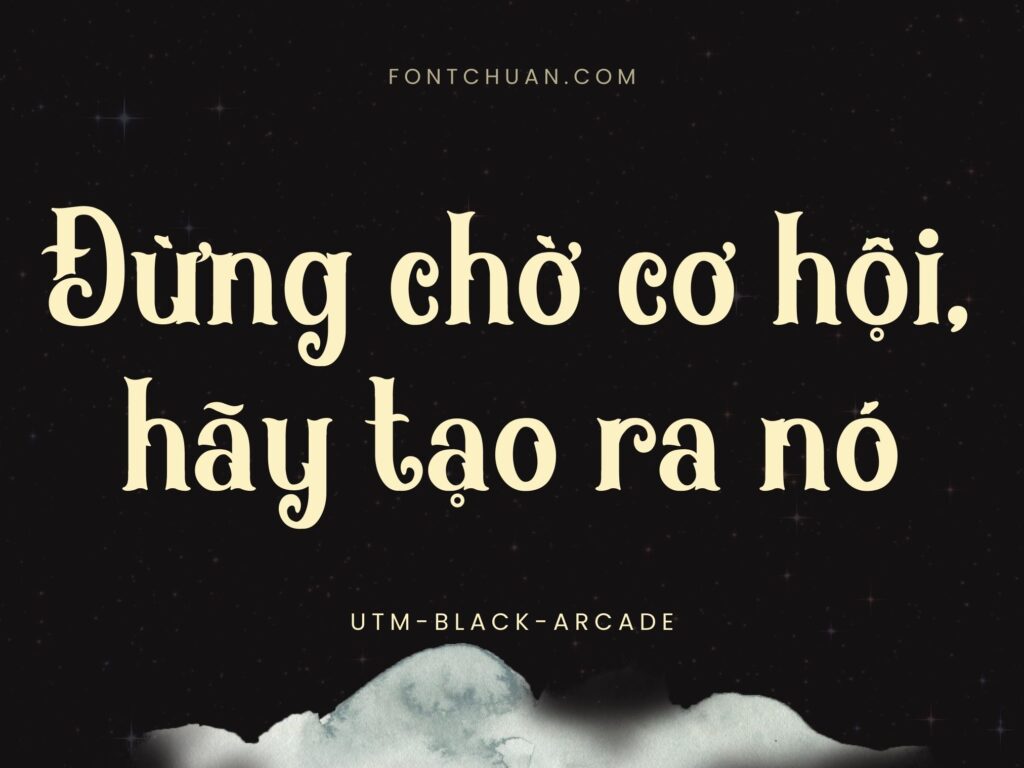
UTM Black Arcade là phiên bản Việt hóa của font chữ Black Arcade, một kiểu chữ decorative mang phong cách Font Vintage, gợi nhớ đến các biển hiệu và tiêu đề từ những năm đầu thế kỷ 20. Font này nổi bật với các ký tự in hoa, đường nét đậm và các chi tiết trang trí độc đáo, tạo cảm giác cổ điển, sang trọng và tinh tế. Phiên bản Việt hóa đã được thực hiện bởi Đinh Kiên, hỗ trợ đầy đủ tiếng Việt cùng hơn 100 ngôn ngữ khác. Đây là một trong những font được cộng đồng thiết kế sưu tầm và chọn lọc nhằm đáp ứng nhu cầu đa dạng trong thiết kế.
UTM Black Arcade có cấu trúc chữ với các nét đậm và chi tiết trang trí tinh xảo, tạo nên sự nổi bật và thu hút. Font này phù hợp cho các ứng dụng như thiết kế tiêu đề, logo, biển hiệu, áp phích và các ấn phẩm in ấn yêu cầu sự cổ điển và nghệ thuật. Ngoài ra, nhờ những đường nét thanh lịch và tinh tế, UTM Black Arcade cũng có thể được sử dụng như một Font chữ spa, mang đến cảm giác thư giãn, sang trọng cho các thương hiệu spa, thẩm mỹ và chăm sóc sức khỏe. Các ngành nghề như quảng cáo, giáo dục, công nghệ và bất động sản đều có thể tận dụng font này để tạo điểm nhấn độc đáo trong thiết kế.